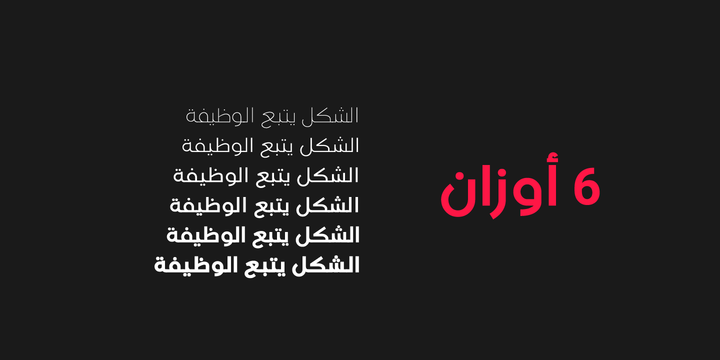
قلم زیبای ارابوتو یک قلم زیبای عربی است که در 6 وزن متفاوت منتشر شده است. این قلم زیبا مناسب پوستر سازی و لوگوتایپ میباشد.
قلم زيباي Araboto Black توسط طراحي و با همت Abd El-Rahman Farahat در وب سايت منتشر شده است. اين قلم در خانواده Araboto-Black منتشر شده است. قوانين استفاده از اين قلم زيبا مي باشد.